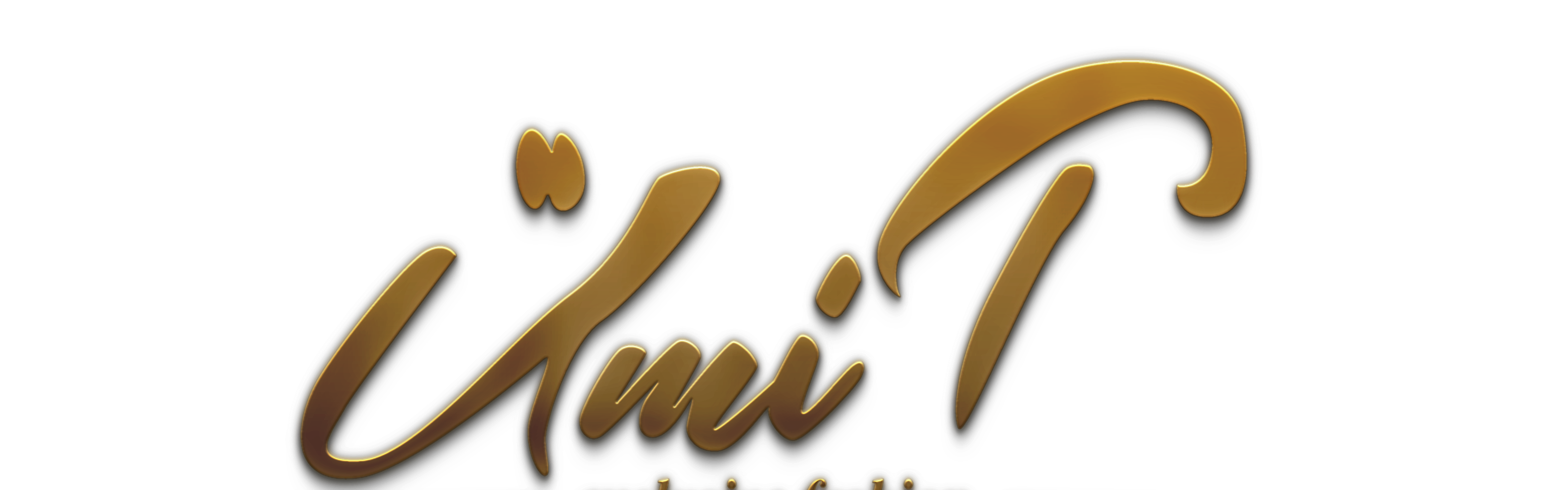
Bulunamayan font
- 17-03-2025, 22:22:54Hocam selamlar, özel bir logo tasarımı da olabilir onun dışında özel bir font da bir kaç yerden baktım benzerleri var ama birebir yok zor bulursunuz.
- 17-03-2025, 22:27:51ilginiz için teşekkürler hocam bizim magazaya çanta yaptırmıştık matbaaya soruyorum brush diyor ama uymuyorercanulucaan adlı üyeden alıntı: mesajı görüntüle
- 17-03-2025, 22:57:49Brush ile uzaktan yakından alakası yok. Özel çizilmişe benziyor hocam.Kocakburak adlı üyeden alıntı: mesajı görüntüle